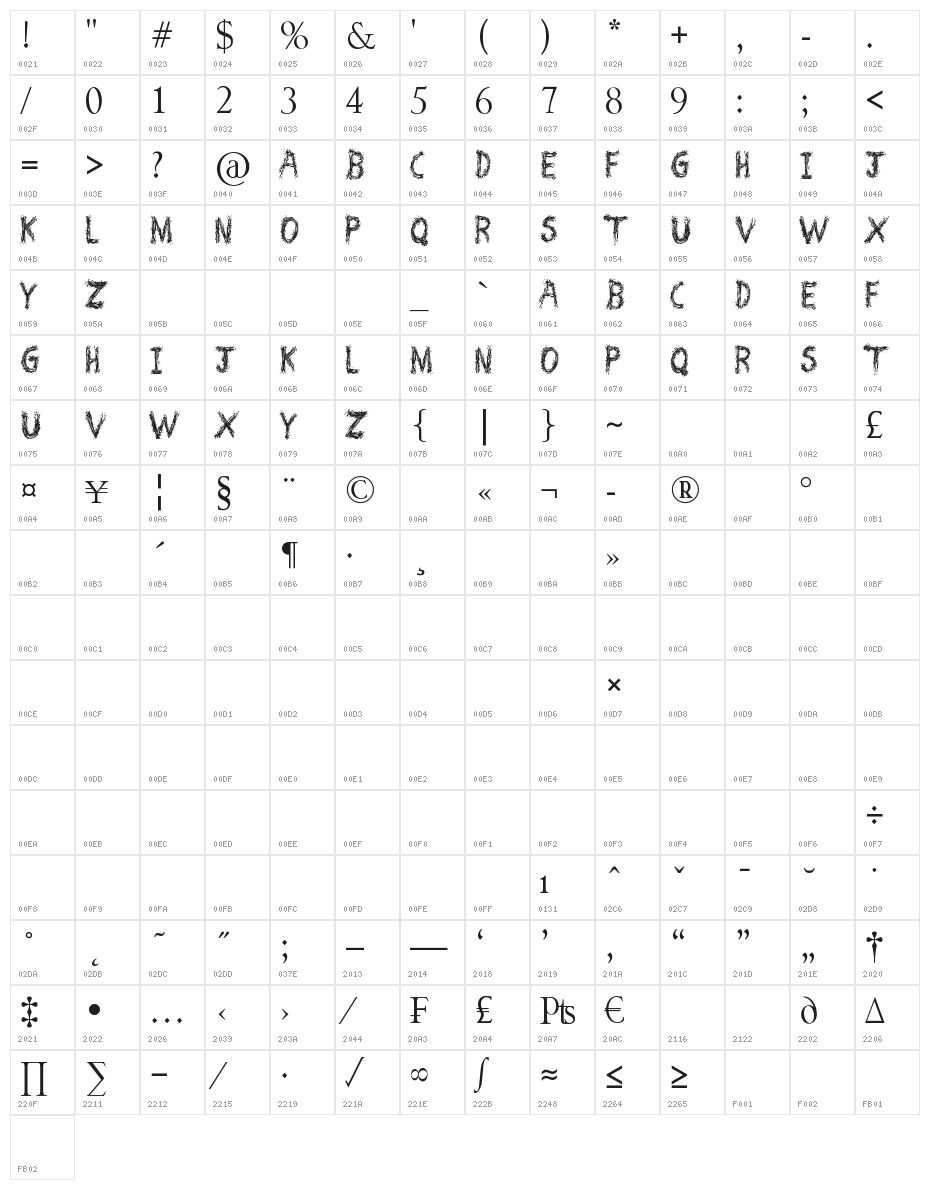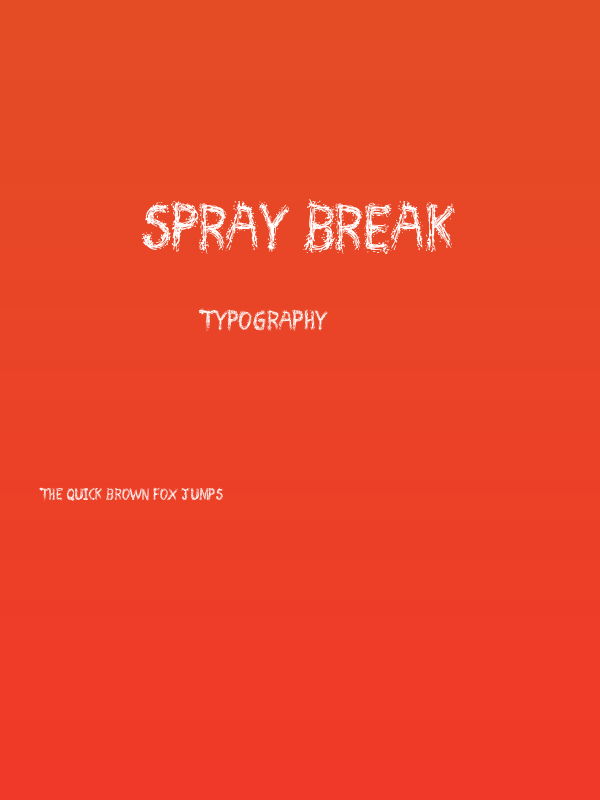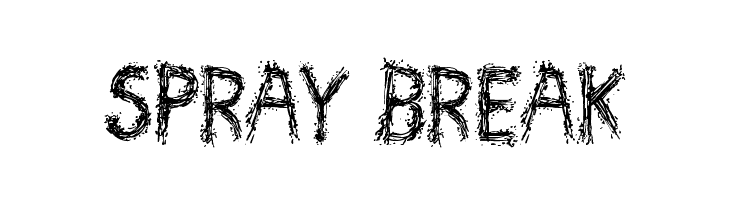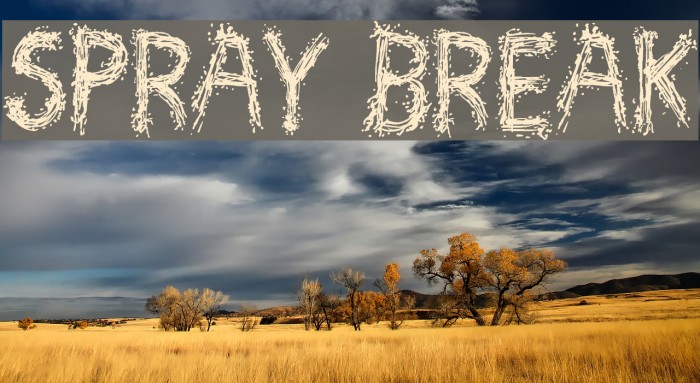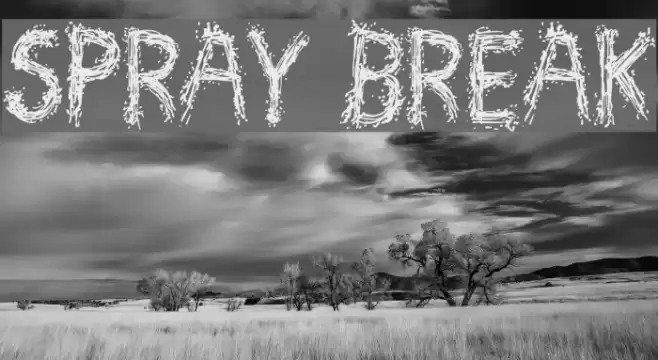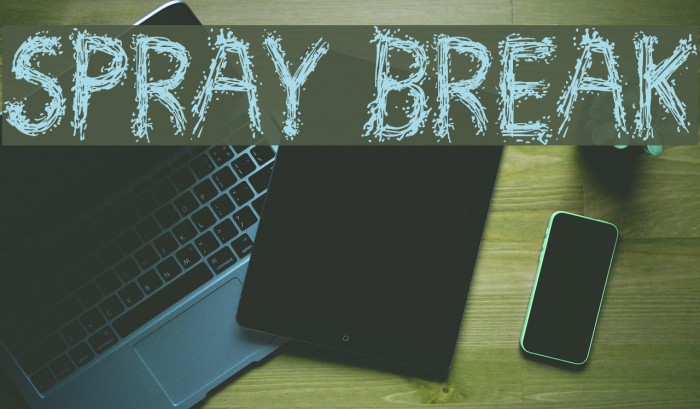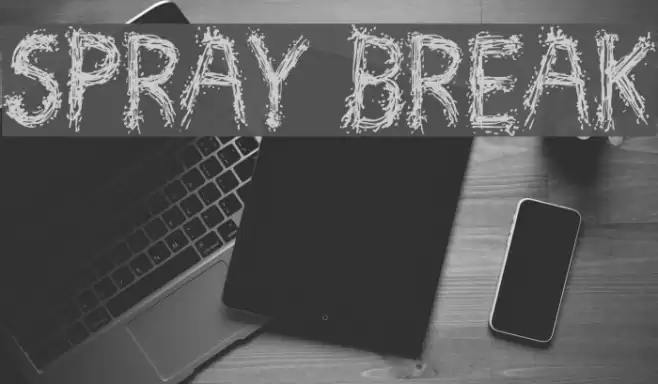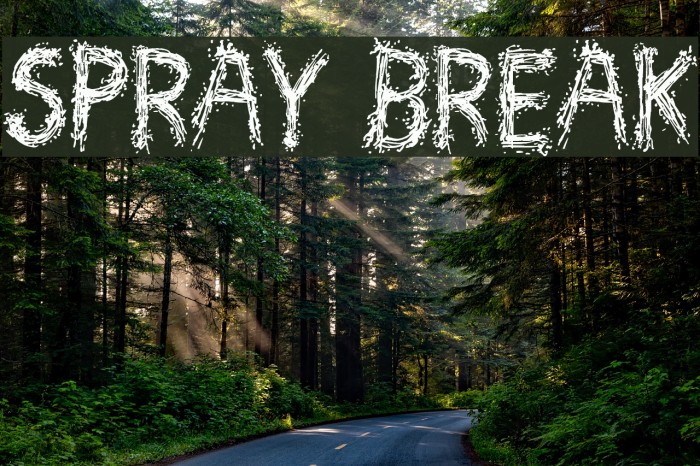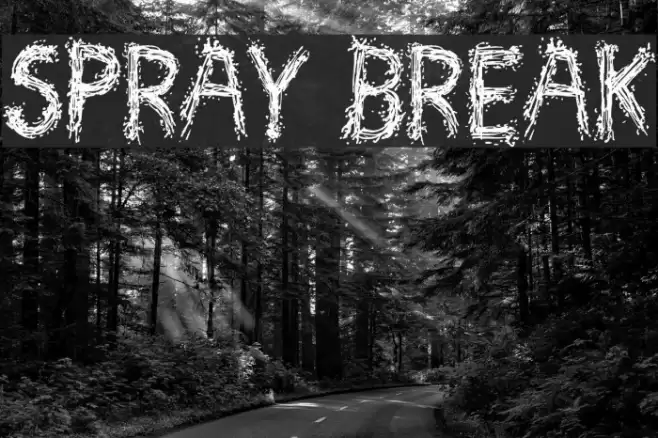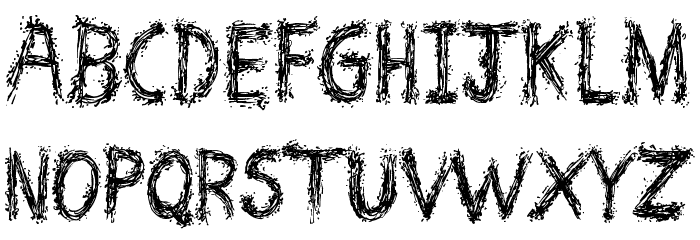
Spray Break Font
✎ Distorted Eroded
| おすすめプロジェクト | Ideal for street art-inspired designs, music album covers, urban-themed posters, and edgy branding projects. |